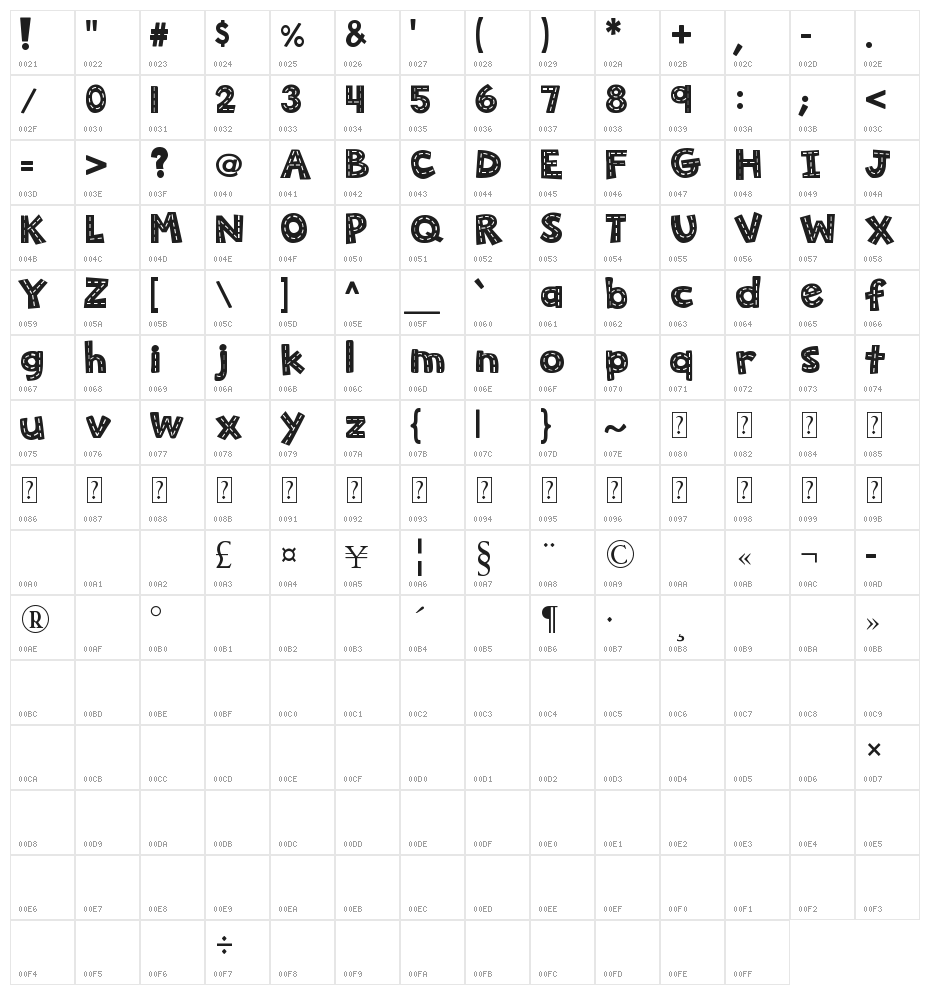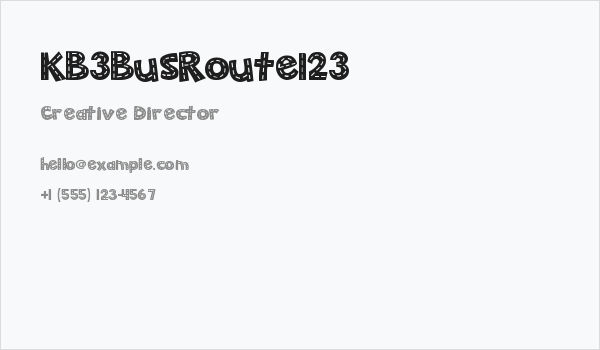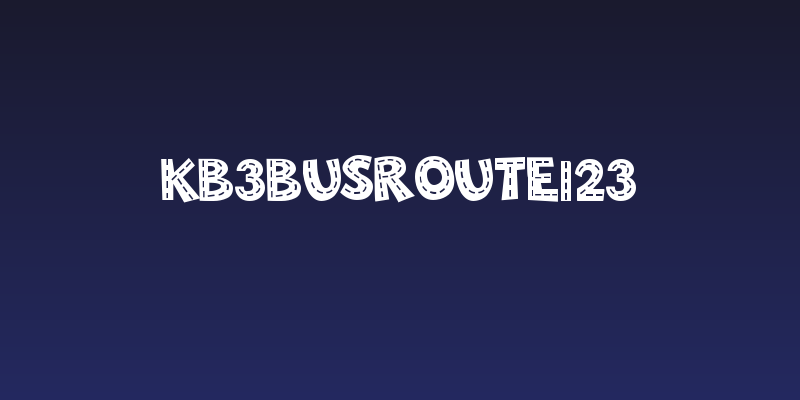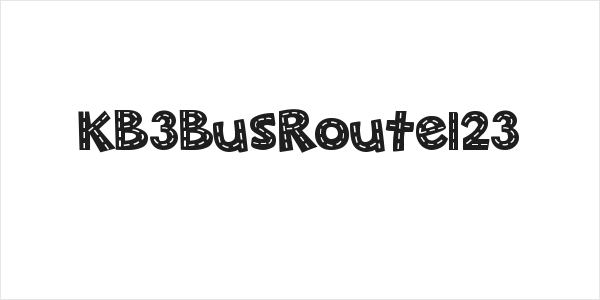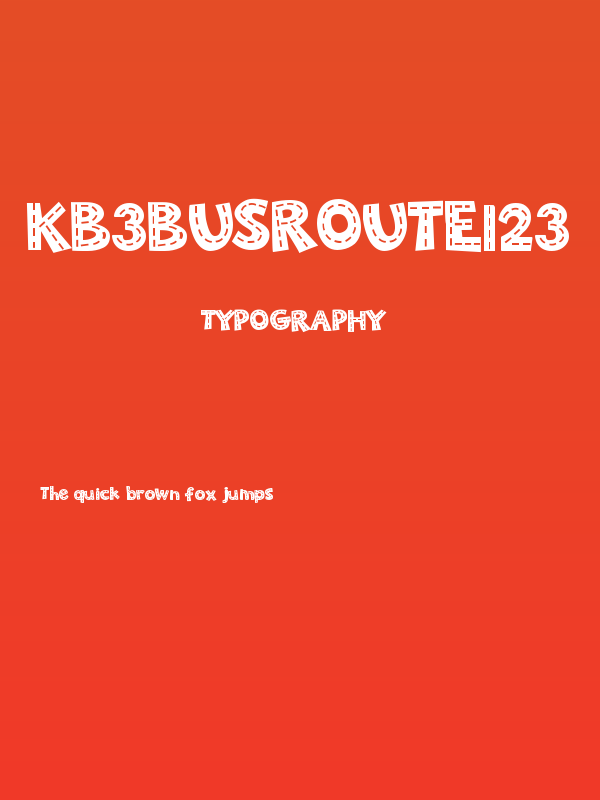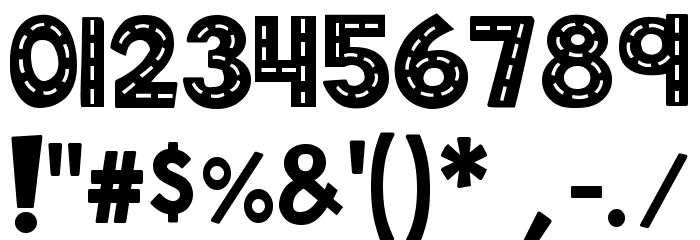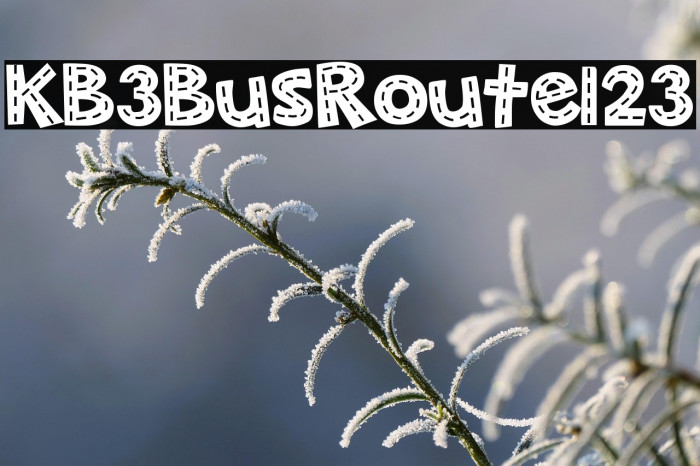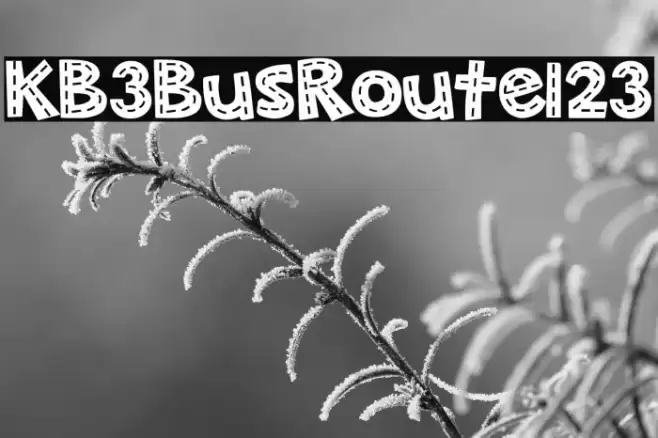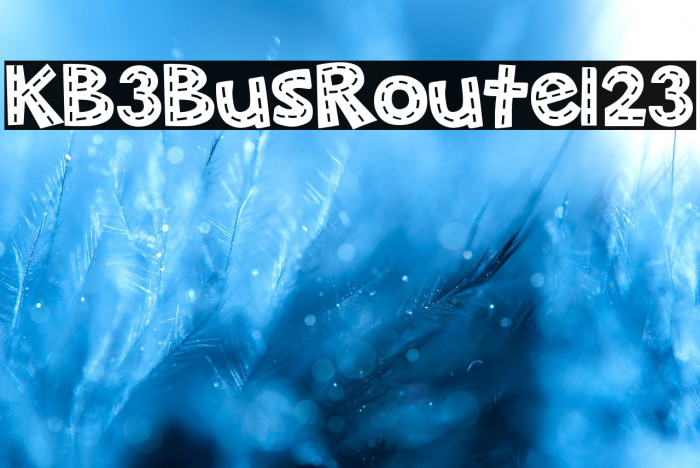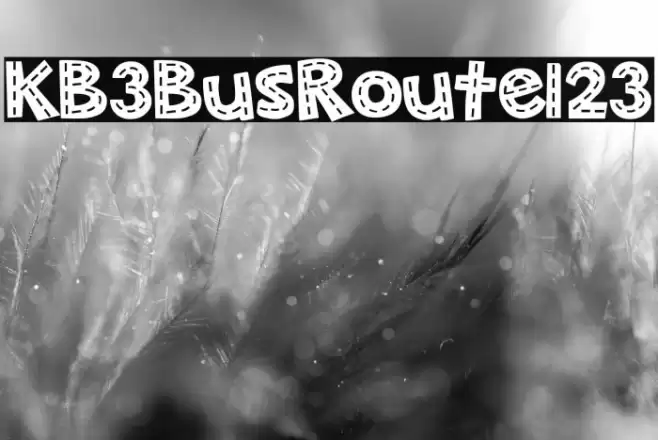
KB3BusRoute123 Font
| Gesamtstil | Playful, Whimsical |
| Vorgeschlagene Projekte | Ideal for children's books, playful branding, party invitations, and creative posters. |